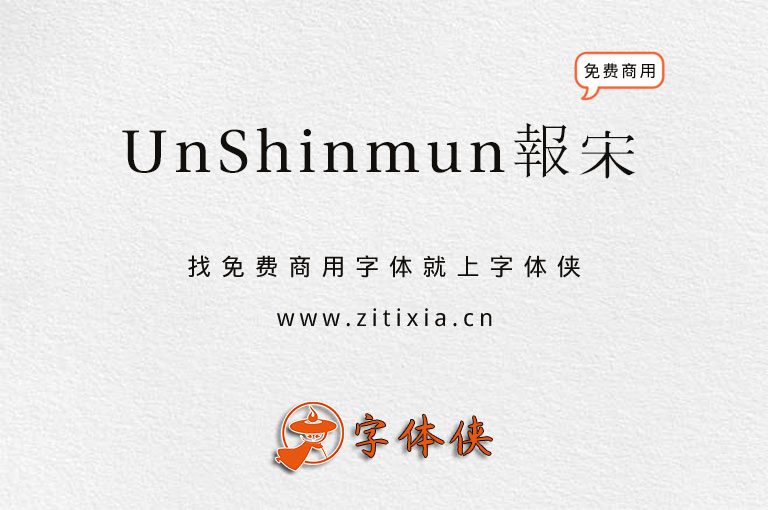
UnShinmun报宋字体简介:
UnShinmun报宋:韩国Un系列开源字体 不一样的宋体旧字形。UnShinmun报宋是韩国Un开源系列字体中的其中一款。这款宋体字形颇有特色,但可惜的是简体字较少,如果遇到缺少字的情况,请以繁体字输入。
韩国Un系列字体是由@Koaunghi Un于1998年以HLaTeX type1制作而成,作者在20世纪90年代末制作type1字体用于韩国的Tex(JLaTex[1]),并以GNU GPL授权许可进行发布。于2003年,由@Won-kyu Park使用FontForge(PfaEdit)转换成ttf文件进行发布。
韩国Un系列字体包括核心系列9款字体和额外系列10款字体,我們将会在稍后的时间逐一进行更新。不过较为可惜的是,这系列字体都是以繁体为主,支持简体的字数较少,中国大陆的小伙伴若要使用这套字体会比较难受。